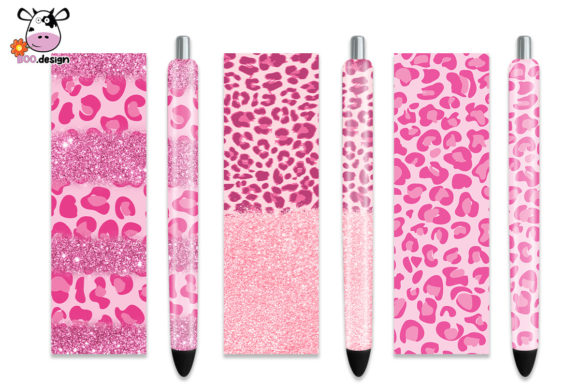
Glitter Pen Wrap
การค้นหาองค์ประกอบการออกแบบที่เหมาะสมอาจเป็นเรื่องท้าทาย แต่ Glitter Pen Wrap นำเสนอคอลเลกชันที่โดดเด่นซึ่งช่วยยกระดับงานของคุณได้ทันที
ไม่ว่าคุณจะสร้างผลิตภัณฑ์ POD (Print on Demand) คำเชิญงานแต่งงาน หรือกราฟิกโซเชียลมีเดีย Glitter Pen Wrap ก็เหมาะสมอย่างยิ่ง